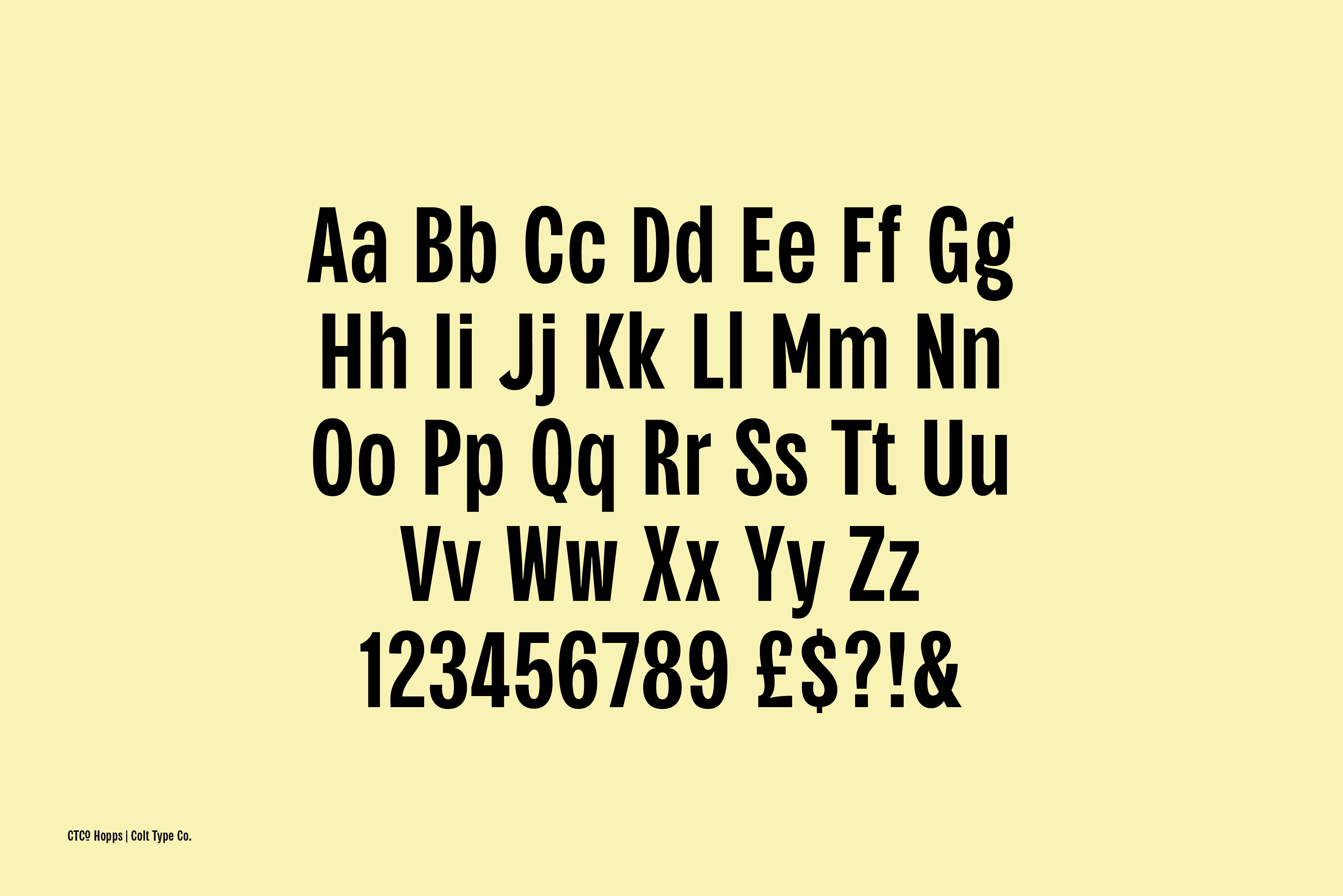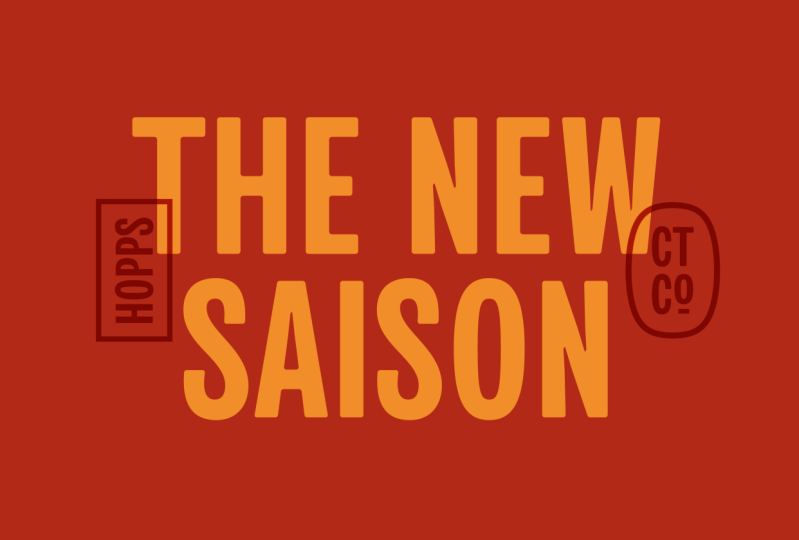
Conception de polices : Se lancer dans la création de polices avec les Glyphes 3 et la typographie
Apprenez à créer votre propre police à l'aide de Glyphs 3.
Si vous êtes novice en matière de création de polices et que vous souhaitez créer vos propres polices, rejoignez-moi pour apprendre à créer et à créer une police professionnelle Dans cette introduction à la création de polices avec Glyphs 3.
Dans ce cours, nous allons décomposer le processus en sections gérables ; de la création de votre dossier Glyphes, au dessin de lettres, en passant par la réalisation de composants réutilisables, en passant par l'espacement, le crénage et enfin l'exportation de votre police.
Si vous êtes nouveau sur Glyphs 3, ce cours est fait pour vous. Vous serez guidés de l'absence de Glyphs 3 à la création et à l'exportation de votre première police utilisée. Une certaine maîtrise de la création de formes vectorielles dans Adobe Illustrator ou similaire sera un avantage, mais pas absolument nécessaire.
• Introduction
• Le projet - Conception et création de votre propre police. Utiliser votre police d'une affiche typographique.
• Esquisse et inspiration - Rassemblez l'inspiration pour votre nouvelle police et réalisez des esquisses. Cela vous donnera une bonne idée de l'aspect de votre police et de la manière dont les lettres pourraient être faites.
• Paramétrer notre dossier glyphes - Nous allons vous expliquer comment paramétrer le dossier glyphes prêt à commencer à dessiner des lettres.
• Dessiner des glyphes carrés - Les formes de lettres sont classées en formes. Nous commençons par des formes carrées.
• Dessiner des glyphes ronds - Ensuite, nous dessinons les lettres rondes.
• Dessiner des glyphes triangles - Les lettres triangles suivent.
• Dessiner des glyphes hybrides - Utiliser les sections des lettres carrées, rondes et triangulaires
• Dessiner le S - Abordons le S qui semble plus compliqué qu'il ne l'est.
• Espacement et bardage - Nos dernières étapes, espacement et bardage permettront d'établir le flux de notre police.
• Tester et exporter votre nouvelle police - Test, test, test ! Utilisez votre police. Tout espacement étrange, tout glyphe écrasant et toute forme impaire se distinguera. Vous verrez que, lors de vos tests, vous affinerez vos formes de polices et votre espacement pour en faire une police belle et bien équilibrée.
1. Introduction: Dans ce cours, nous allons créer des polices san-serif en majuscules Je m'appelle Adam. Je suis designer de marque et je possède également une fonderie de caractères indépendante Il y a dix ans, j'ai commencé à créer des polices de caractères. C'est après avoir visionné le documentaire Helvetica que nous avons vu toutes ces fonderies et créateurs de caractères parler avec passion des polices de caractères , de la façon dont elles les fabriquent et de ce qui les inspire Et cela a déclenché quelque chose dans ma tête. J'ai soudain pensé que je pouvais aussi faire une chute. Sous ma voiture de fonderie à froid. J'ai probablement créé une vingtaine de polices, c'est loin. Et cela va des formes géométriques aux types de pinceaux. Si vous allez consulter mon profil, vous verrez des liens vers ceux qui s'y trouvent. Si vous êtes graphiste ou artiste de lettrage. Et en matière de conception de polices, c'est un très bon ajout à vos compétences . Ce cours s'adresse à tous ceux qui découvrent le logiciel de glyphes et la nouvelle conception des polices Ensemble. Pendant que nous créons notre police, nous passerons en revue le logiciel Glyphs et apprendrons à utiliser les fonctions de base À la fin du cours, vous aurez donc une très bonne idée du fonctionnement des glyphes, mais surtout, vous saurez comment créer une police rose. L'objectif est de vous donner une bonne introduction aux glyphes et de vous aider à démarrer votre aventure, il s'agit d'un design de police J'espère donc que tu me rejoindras. 2. Le Projet: Le projet Amen consiste à créer une police et nous allons le faire pendant que nous apprenons à utiliser les glyphes. Au fur et à mesure que nous apprendrons , nous construirons notre police Une fois créé, quel meilleur moyen de le mettre en valeur que de créer une affiche typographique ou peut-être même un ensemble de types de prothèses de produits. Ce que j'aimerais voir dans vos affiches, c'est quoi ressemble votre travail, à quoi il ressemble, comment se comporte-t-il et comment il agit ? Nous allons diviser ce cours en sections faciles. Nous allons commencer par dessiner et planifier notre police de caractères. Une fois que nous aurons réglé tout cela, nous configurerons notre fichier de glyphes Ensuite, nous allons commencer à créer notre ensemble de personnages principaux. Passons aux chiffres et à la ponctuation. Sans jeu de caractères complet, nous examinerons l'espacement et le crénage, puis passerons aux tests. Une fois que nous avons testé et exporté, c'est tout. Nous avons terminé. Nous avons notre police complète en classe. Suivez chaque leçon. Si vous voulez créer exactement le même style de police que moi, ou si vous vous sentez un peu plus aventureux, créez quelque chose de nouveau J'adorerais voir ce que tu trouveras. N'oubliez pas de télécharger la partie d'introduction depuis la section des ressources ci-dessous. J'ai ajouté quelques aide-mémoire qui vous aideront vraiment à démarrer dans l' apprentissage des touches de choc Cela vous aidera à accélérer votre processus dès maintenant et j'essaierai de me référer à ces clés au fur et à mesure. N'oubliez pas de créer un projet de classe. Montrez-nous que la nouvelle police que vous avez créée montre les affiches typographiques mettant en valeur votre police Je suis vraiment impatiente de voir ce que tu as fait. Si tu ne l'as pas déjà fait. Installons Glyphs Three pour le moment Un essai gratuit de 30 jours est disponible sur le site Web Et préparons-nous à MX Dot 3. Croquis et inspiration: Avant de commencer à concevoir notre formulaire, puisons notre inspiration dans des livres de typographie, des magazines ou des spécimens de typographie, ou même de n'importe quel endroit sur Internet où vous avez vu une belle topographie et fait quelques croquis Savoir où vous voulez que votre police soit utilisée et comment vous voulez qu'elle soit utilisée sera un énorme avantage lorsque nous concevons réellement dans Glyphs Un pack d'introduction est disponible à télécharger via Skillshare Dans le pack d'introduction, vous trouverez un modèle de carnet de croquis déjà des lignes de mesures Vous trouverez également un fichier de glyphes , préfabriqué avec tous les caractères que nous allons utiliser Et vous trouverez un aide-mémoire sur les glyphes avec toutes les touches de raccourci répertoriées Alors faites un croquis et quand nous serons prêts, nous configurerons notre premier fichier de police 4. Mettre en place notre dossier pour les glyphes: Commençons par créer notre fichier de glyphes. Tout d'abord, nous allons choisir Nouveau fichier et faire défiler la page jusqu'au latin. Donc, des glyphes non préparés pour vérifier les bases et créer un fichier Cette police sera uniquement en majuscules, nous allons donc supprimer les minuscules Dans le panneau de gauche. Vous pouvez passer en revue tous les caractères que vous souhaitez ajouter à votre police. Dans le téléchargement du pack d'introduction, vous trouverez le fichier de glyphes prêt à être utilisé qui a été préparé pour cette leçon Si vous ouvrez le modèle Eclipse à partir du pack d'introduction, voici ce que vous verrez Faisons-en profiter. Le panneau d'information. Je pense que l'alcool, c'est pour les fils d'Adam. Les unités par mètre conserveront milliers de versions, c'est juste au moment où vous modifiez la nouvelle version, assurez-vous d'ajouter un axe Y et de mettre à jour les fonctionnalités Sur le master. Nous pouvons voir le nom de notre maître. La nôtre est régulière. La façon dont nous allons passer à 400. Et vous pouvez également consulter les valeurs de nos métriques. Pour ce point, j'aimerais utiliser une valeur de dépassement d'environ 16 unités Pour chaque métrique. Il s'agira d'une bordure ou d'une marge. 16 unités. Pour le dépassement Il existe de nombreux plug-ins pour les glyphes. Et une chose que je ne peux pas faire, c'est montrer l'épaisseur de la tige. Donc, si vous allez dans Plug-in Manager, vous pouvez faire défiler la page vers le bas ou rechercher une certaine épaisseur de tige. Puis cliquez sur Installer. De toute évidence, je l' ai déjà installé. Donc, une fois que vous l'avez installé, redémarrez glyphs et il sera activé Et l'épaisseur de votre tige vous donne une idée de la façon dont la tige est une section. Pour celui-ci, vous pouvez voir qu'il s'agit d'une largeur de 146 unités. Vous pourriez tout simplement utiliser la règle. Mais c'est une chose supplémentaire que vous devez activer et désactiver. Alors que l' épaisseur de la tige du rivage est toujours la même. Et cela ne fait que rendre la vie un peu plus facile. Si vous ne voyez pas l'épaisseur de la tige Schar fonctionner. Accédez simplement à Afficher , puis activez Afficher l' épaisseur de la tige sous Afficher. Maintenant, configurons notre fichier et une fois qu'il est enregistré, nous sommes prêts à partir et les choses amusantes commencent. Donc, dans la prochaine leçon, nous allons voir comment créer nos glyphes carrés N'oubliez pas que si vous êtes bloqué à un moment ou à un autre, je suis disponible dans le panel de discussion sur Skillshare Je te verrai dans la prochaine leçon. 5. Dessiner des glyphes carrés: Il est bon de regrouper les glyphes par forme. Nous avons des rectangles, des cercles et des triangles. Si nous les regroupons, c'est parce que nous utiliserons des éléments de ces glyphes pour refaire d'autres Vous devriez toujours essayer de commencer par une haie. Il établit la largeur, la hauteur et l'épaisseur de la tige. découvrirons que la tige de la haie est la pièce que nous allons le plus souvent copier-coller dans de nouveaux glyphes Pour celui-ci, je vais utiliser une épaisseur de tige de 160. Je vais dupliquer cette tige pour créer les deux côtés de la haie. À l'aide des touches fléchées et de l'outil d'épaisseur de la tige. Nous pouvons parfaitement espacer nos tiges. Ajoutons maintenant la tige horizontale. Elle sera légèrement plus fine que la tige verticale. Pour l'équilibre optique. La tige verticale mesure un sixième, je vais donc taper 150 pour la tige horizontale En utilisant la barre d'espace, nous pouvons prévisualiser le vaisseau. Maintenant, nous avons fait la haie. Nous pouvons passer à la création de l'œil et d'autres personnages carrés. Copions cette tige de la haie et nous l'utiliserons pour fabriquer notre œil. Nous allons maintenant établir que E, F et L. Le F et le L partageaient la plupart des caractéristiques du genou. Nous allons donc commencer par un a. Encore une fois, en utilisant la haie. Nous utiliserons la tige de haie et la barre horizontale de la haie. Nous allons copier ce n vers le e pour voir si votre nœud est parfaitement aligné avec la ligne métrique. Et il affichera soit un cercle, soit un diamant. Un cercle signifie qu'il se trouve dans la limite du dépassement S'il y a un diamant, il correspond parfaitement au e et a l'air bien. Nous pouvons maintenant utiliser les éléments du E pour créer rapidement le F et le Al. C'est donc notre haie, E, F et L en colère, reste plus qu'un T. T. qui utilise exactement les mêmes principes que ceux que nous avons établis pour tout le reste ici. Je vous laisse donc le soin de le faire vous-même. 6. Dessiner des glyphes ronds: Pour faire nos lettres rondes, nous allons évidemment commencer par le 0. Et pour trouver la largeur et l' épaisseur, vous utiliserez la haie. En utilisant la haie comme guide, je vais faire un ovale. Pour des raisons d'équilibre optique, il est probable que vos lettres rondes aient besoin d'un certain dépassement Et c'est là que nos 16 points de dépassement entrent en jeu Maintenant, je vais dupliquer cette forme pour faire le compteur du, oh, je vais la redimensionner pour m'assurer qu'elle correspond à toutes les largeurs, ou même en sélectionner les deux parties Ou je découperai la forme en utilisant commande et le X et je la collerai à nouveau dans notre glyphe Les courbes sont actuellement téléchargées La courbe la mieux ajustée aide vraiment à égaliser ces courbes. L'idée qui sous-tend l'outil d'ajustement de la courbe est qu'il utilise une échelle de pourcentage pour modifier la quantité de courbe entre deux nœuds. À l'aide de la commande, de l'option, de la commande et des chiffres de un à huit, vous pouvez modifier la valeur de cette courbe d'ajustement afin qu'elle corresponde aux points situés sous les pourcentages dans l'outil de courbe d'ajustement Nous avons un petit problème avec la Terre. Il est rempli, et c'est parce que indications du chemin sont erronées. Nous pouvons le constater par les flèches pointant toutes deux vers la droite. Un intérieur doit aller dans le sens des aiguilles d'une montre. Un externe doit aller dans le sens antihoraire. Il existe plusieurs manières de modifier les directions du chemin. La première consiste à sélectionner le chemin. Cliquez avec le bouton droit et inversez les contours sélectionnés. Ou nous pouvons sélectionner tous les chemins dans le glyphe. Va sur le chemin. Et la bonne direction du chemin. Je préfère utiliser la bonne direction du chemin. Je pense qu'il vaut mieux laisser glyphes déterminer le chemin à suivre , car nous sommes maintenant sur la mer Intéressons-le en tant que composant. Je vais décomposer le 0 et en découper une section dans l'air pour former notre forme en C. Faisons la file d'attente. Encore une fois, nous allons l'ajouter en tant que composant, mais cette fois, il restera en tant que composant et nous n'y toucherons pas. Tout ce que nous allons ajouter, c'est la queue de la file d'attente. Le fait de conserver le composant signifie que si nous apportons des modifications à notre original, ces modifications seront également apportées dans la file d'attente. Je vais commencer par le C pour donner à notre G l' importance en tant que composant et le décomposer à nouveau. Nous pouvons prendre la tige horizontale d' une haie et la placer dans notre GI, aligner le tout et nous assurer que tout est beau, net et équilibré. Utiliser l'outil d'ajustement des courbes pour conserver la cohérence de toutes ces courbes 7. Dessiner des glyphes triangulaires: Dans cette leçon, nous allons examiner les lettres triangulaires. Pour moi, c'est a, V, K, M, N et W. J' aime commencer par un air pour mes lettres triangulaires. Je vais copier-coller la tige de la haie , puis l'incliner pour obtenir une diagonale parfaite. Utiliser la haie comme référence pour la largeur. Je vais déplacer la tige d'air dans la bonne position , la dupliquer, puis la retourner horizontalement pour créer l' autre côté de l'air. Lorsque vous assemblez deux lignes de cette façon, le haut peut paraître un peu plus gros que le bas Nous l'avons donc placé en haut pour lui donner un aspect plus équilibré et un peu plus uniforme. J'utiliserai la barre de la haie pour la placer en l' air et je la mettrai simplement en place. L'air semble un peu mince. Je pense donc que je vais déplacer ces lignes extérieures plus loin et réduire la largeur de la barre. Je veux que la section triangulaire de l'air soit aussi nette que possible, mais je voulais tout de même en avoir un certain contrôle. Je vais donc joindre les deux pièces. Mais avec ce nœud au milieu, je veux pouvoir contrôler indépendamment les angles gauche et droit. Et comme vous pouvez le constater, avoir un seul nœud n'est pas si simple. Nous pouvons donc utiliser un coin ouvert comme celui-ci pour simplement déplacer une section à la fois ou une ligne à la fois. C'est rarement utile dans les virages où vous devez déplacer des objets assez souvent. Cela signifie que vous ne déplacez qu'une seule pièce au lieu de deux pièces. Je veux que cette section soit exactement la même que le V. Je vais donc créer un composant à partir de cette pièce. Donc, si vous le sélectionnez, puis passez au composant depuis la sélection, puis que vous l'appelez quelque chose dont vous vous souviendrez. Et cela crée un nouveau glyphe. Ensuite, si nous passons à notre V, nous pouvons ajouter ce nouveau composant dans le glyphe Ensuite, sélectionnez-le et retournez-le horizontalement. Nous avons là notre B parce que c'est un composant. Si nous voulons changer quoi que ce soit pour l'air, se reflète également dans la façon dont j'aime les avoir sur LinkedIn de cette façon. Juste pour qu'il y ait une cohérence entre ces deux personnages. Pour le W, nous allons utiliser le même composant comme point de départ. Mais au lieu d'utiliser le composant tel quel, nous allons le décomposer Nous avons donc ces deux composants ici maintenant, mais nous ne pouvons pas les déplacer car ils prennent les valeurs de notre glyphe initial à partir de ce composant, Ces composants sont configurés pour s'aligner automatiquement. Si nous voulons les déplacer, nous devons désactiver l'alignement automatique. Si nous cliquons avec le bouton droit de la souris et que nous désactivons l'alignement automatique, cela nous donnera un contrôle total du mouvement. Nous pourrions donc simplement les assembler comme ça. Mais notre police est assez étroite. Cette version large de w aurait donc l'air étrange et déplacée. Donc, ce que nous allons faire, c'est le décomposer et écraser pour qu'il corresponde davantage au type que nous avons déjà créé. davantage au type que nous avons déjà créé Travaillons ensuite sur m et n. Je vais utiliser la haie pour déterminer la largeur de l'extrémité, correcte ? Réponse. Créez la section diagonale. Je vais le dupliquer, l'une des tiges et passer simplement sur les nœuds. Cela voudra être plus fin. J'aime donc simplement déplacer un peu plus les nœuds. Je trouve que ça a l'air plutôt bien. Je vais donc copier tout cela et m'en servir, la majorité d'entre eux. Mais évidemment, l'amnésique doit être un peu plus large. Pas trop loin là-bas. Nous venons de sortir de la marge. Mettons donc marge positive là-dedans , juste pour être sûrs de pouvoir voir ce que nous faisons. Je vais utiliser cette tige centrale, copier, la coller, puis la retourner horizontalement et la placer. Juste, et c'est ce que cette vérification permet de vérifier où tout se trouve. Ensuite, je veux fusionner tout cela. Retirez les deux nœuds situés en bas. Juste pour créer notre forme en M et y ajouter à nouveau un coin ouvert, il est toujours bon d'ajouter un coin ouvert où se trouve une section comme celle-ci. Il a l'air un peu large, donc je vais juste y apporter une touche. L'argent devrait être relativement facile. Je vais commencer par le Je n'ai pas besoin du jour. Il suffit de prendre la tige et le pied du R. Et nous allons juste les utiliser pour les soins. Comme vous pouvez le constater, la majeure partie s'y trouve déjà. Juste moi, déplace cette pièce à peu près au centre. Sélectionnez tout, copiez-le et collez-le, puis retournez-le verticalement ou horizontalement. Lieu de passe-temps. Très beau soin. J'en suis content. Pour terminer, je vais simplement fusionner ces deux pièces et les ajouter dans ce coin ouvert. Déplace ça dedans. Ensuite, nous y installerons également celui-ci. Juste pour donner l'impression que c'est vraiment connecté. Nous progressons vraiment bien et il ne nous reste que quelques lettres. 8. Dessiner des lettres hybrides: Viennent ensuite les lettres hybrides. C'est ici que nous combinons des éléments de nos glyphes carrés et des éléments de nos ascenseurs ronds pour créer des glyphes ronds carrés, tels que a, D, P, R et B. Je vais commencer par D en utilisant des sections de i, et nous allons créer cette forme en D. Je vais copier-coller ce que j'ai trouvé dans le D. Et en sélectionnant uniquement les nœuds de droite à partir du 0, les copier et les coller également dans le glyphe D. Une fois ceux-ci en place, je vais les réaligner. Nous n'avons pas besoin de dépasser un D, il suffit de nous assurer qu' ils sont parfaitement alignés Encore une fois, en utilisant cette forme de diamant comme référence. Je le ferai pour le haut et bien sûr pour le bas. Ensuite, nous devons étendre cette forme sur la droite pour en faire une forme solide pour le moment, elle n'est pas connectée. Nous devons donc nous assurer qu'il est connecté. Et nous le faisons avec le stylo. Et cela en utilisant la touche de raccourci P. Et tracez simplement quelques lignes et reliez cette forme. Je vais faire de même pour le bas. Sélectionnez le premier nœud , puis joignez le tout. Et vous pouvez voir que ce vaisseau a maintenant pris sa forme complète. Quand c'est rempli comme ça, vous pouvez voir que tout est connecté. C'est notre forme en D. Avec juste quelques ajustements, vous vous assurerez que tout est beau, équilibré et correct À partir du D, nous pouvons ensuite créer une forme de pois. Je vais copier-coller le D dans le p.ball. Je vais sélectionner cette courbe et redimensionner pour créer la courbe du p. J'utilise les flèches haut en bas pour obtenir toutes ces largeurs, C'est là que le plugin Shore Stem Thickness s' avère très pratique, car nous pouvons voir toutes ces épaisseurs lorsque nous déplaçons ces nœuds Nous n'avons pas besoin d'activer un autre outil pour le voir en peaufinant un peu plus ces nœuds Et nous sommes prêts à le faire. Essentiellement, le R n'est que le P avec une jambe. Nous allons donc ajouter le p. puis dessiner. J'aime bien, j'aime utiliser l'outil du rectangle. Ensuite, sélectionnez simplement les deux nœuds inférieurs et faites-les glisser vers l'extérieur. Toi et J, je vais m'en sortir avec la haie. En commençant par vous, je vais copier cette tige de la haie. Je vais copier le plus qui entre dans l'UE. Ensuite, j'utilise le 0 comme guide pour la largeur de l'UE. Ensuite, nous allons construire le u en utilisant ces sections. Le bas de l' UE est trop haut. C'est parce que nous l'avons emprunté au R. Ce que nous voulons, c'est qu'il ressemble davantage à la courbure du d. Et nous pouvons le faire en ramenant les nœuds un peu plus près du bas. Ensuite, en utilisant notre outil de courbe d' ajustement, qui est Control Option Command. Et j'en utilise sept. Nous pouvons rendre ces courbes belles et nettes. Encore une fois. Pour créer le j, nous pouvons utiliser le u. Copiez-le et collez-le en l'air. Ensuite, nous allons simplement supprimer les nœuds de gauche Coupe-le juste là, en angle. Supprimez-les et ils auront notre J. Pour le y. Nous allons réutiliser notre composant. Nous allons le retourner puis le décomposer. C'est. On dirait ces nœuds et mettez-les en position. En utilisant la tige de l'œil. Nous allons copier-coller ces deux objets dans notre centre y. Ensuite, je vais nettoyer ces deux nœuds et nous aurons un y à ajouter Utilisons un t. Je vais copier-coller le haut du T et le dupliquer vers le bas pour le zed. Copiez ensuite le radical du T et utilisez-le pour la partie diagramme de cette annonce. Et x peut être assez difficile à créer. Mais pour ce style de police, je préfère utiliser la forme diagonale que nous avons déjà créée, la décomposer puis la réduire. Je vais ensuite le copier et le coller en place, en le reproduisant essentiellement pour créer un X. Sélectionnez tout, assurez-vous qu'il correspond à la hauteur du capuchon. Une fusion. N'oubliez pas de remettre ces coins ouverts une fois de plus. Je vais juste tout emménager pour qu'il convienne. Le reste de la police. Je vais les mélanger et créer de très jolis 9. Leçon 8 Le S: S peut être une autre lettre difficile, mais décomposons-la en sections. Nous allons utiliser un C. Nous n' utilisons que la partie supérieure de la mer. Nous allons donc le copier-coller et déplacer ces nœuds en place. Nous allons corriger ces courbes douteuses en utilisant la méthode de la courbe d'ajustement Maintenant, copiez-collez notre haut dans le bas. Il suffit de le retourner et de le placer dans la zone de dépassement Nous devons maintenant réunir ces deux pièces. Nous allons donc créer un lien entre le haut et le bas. Lorsque nous aurons mis en place un lien de base, tout le groupe émergera-t-il dans son ensemble. À ce stade, c'est une bonne idée de corriger la direction du chemin. Ces nœuds carrés bleus indiquent qu'il peut s'agir de coins. Donc, ce que nous voulons faire, c'est double-cliquer dessus et les transformer en lignes continues. Cela facilite le flux de la lettre. Il ne nous reste plus qu' à mettre nos nœuds et bras en place pour faire de beaux numéros Nous avons maintenant dessiné toutes les lettres majuscules. Nous avons toutes les connaissances nécessaires pour créer le reste de nos personnages. Je vous laisse donc le soin des chiffres et de la ponctuation. Et je te reverrai ici pour l'espacement et le crénage 10. Espacement et crénage: Nous avons donc maintenant toutes nos lettres en place. Nous pouvons maintenant commencer, l' espacement est bon d' utiliser des groupes d'espacement. Nous allons donc utiliser la haie et un R et un V, ou un héritier, pour créer de l'espace en groupe. Pour nos glyphes rectilignes, je vais utiliser Hedge Pour une haie. Donnons-lui une valeur de six jours. Nous le ferons pour les deux parties. Et un moyen simple de reproduire les deux versions consiste à utiliser des valeurs égales. Et cela prendra la valeur du côté gauche et l'utilisera également du côté droit Nous pouvons maintenant appliquer la même valeur, couverture, à i, m et n. En sélectionnant tous ces caractères, nous pouvons descendre en bas à gauche et saisir les valeurs de ces roulements latéraux. Nous allons simplement saisir « haie » dans les deux valeurs des roulements latéraux. Nous pouvons donc voir ici que le nombre de favoris est égal à celui d'une haie , soit 60 points Pour nos lettres rondes, nous utiliserons le R. Nous pouvons soit y mettre une valeur numérique, soit utiliser notre valeur comme norme pour les autres lettres incurvées. Ou nous pouvons utiliser une équation. J'aime parfois utiliser. La moitié de la haie. Mettez fin à l'équation de h sur deux, ce qui nous donne alors 30 points. Encore une fois, sur le côté droit, barre égale nous donnera également une valeur de 30 points sur le côté droit Il suffit de les tester en appuyant plusieurs fois sur la haie. Nous pouvons voir à quoi ressemblent ces espaces. Nous pouvons appliquer les valeurs à Q, C, G, zéro et parfois à un S, selon la proximité de la courbe avec un 0. Je vais utiliser V comme maître. Mais il ne faut pas oublier de désactiver l'alignement automatique dans cet air libre Et le V. A V possède beaucoup d'espace négatif. Nous allons donc lui donner une petite valeur sur les roulements latéraux. Nous pouvons appliquer cela au y et à l'air, et parfois aussi au w, au x et au t. Et ils nous permettent d'utiliser la valeur de haie sur le côté droit et la valeur 0 sur le côté incurvé pour les côtés valeur de haie sur le côté droit et la valeur 0 sur droits. Bien entendu, vous pouvez simplement utiliser des valeurs pour les glyphes de votre choix Vous n'êtes pas obligé de les regrouper. Je trouve juste que cela nous facilite beaucoup la vie si nous avons des groupes sur le L. Je me débrouille tout seul avec 16. Mais sur le côté gauche, il a une valeur de couverture Parce que W a un espace négatif légèrement inférieur un V. Mais nous voulons tout de même utiliser la valeur V. Nous pouvons simplement utiliser une équation comme V plus dix. Et cela nous donnera la valeur v avec dix points supplémentaires Lors de l'espacement, vérifiez régulièrement les caractères. Appuyez sur la commande Option F pour afficher les chaînes de texte. Ils sont très utiles pour vérifier espacement et voir s'il vous manque des glyphes Comme pour les groupes d'espacement, nous pouvons également créer des groupes de crénage Vendons des groupes de crénage. Donc, pour une, je vais donner de l'air à ce groupe de comptabilité. Cela peut également s'appliquer au y ou au T. Et pour v, je vais lui donner une valeur de crénage, notre groupe comptable de v également Ensuite, entre le a et le v, nous pouvons faire en sorte que ce soit -20 ou peut-être plus. Il faudra peut-être plus que cela. Si nous regardons le bas de notre panneau de glyphes, nous pouvons modifier le flou du texte. Et cela nous permet de voir l'espace négatif entre chaque lettre. Comme vous pouvez le voir ici, il y a un peu trop de distance entre le a et le v par rapport à la haie et à la haie. Faisons donc en sorte que ce point soit défectueux, juste pour réduire un peu plus cet écart. C'est une très bonne technique juste pour voir quels sont ces espaces négatifs. Maintenant, nous allons faire correspondre l'autre côté du V et l'air. Et évidemment, cela devrait être un -40. Si nous tapons a et V plusieurs fois, nous pouvons voir que cet espacement est cohérent Maintenant, nous allons faire le W. Si nous appliquons la valeur du groupe V à w, nous pouvons voir que cela la fait également entrer de -40 Cependant, je pense que c'est peut-être un peu trop. Donnons donc ceci, c'est basé sur la valeur, et nous allons faire en sorte que ce soit -30 Et faites de même sur le côté droit. Le courant des groupes peut être appliqué à n'importe quelle lettre. Appliquons donc le groupe V au y. Vous pouvez voir que cela donne les mêmes valeurs que pour le V et l'air. Nous allons donc nous frayer un chemin en créant du courant par paires et en créant des groupes au fur Cornyn et espacement protègent le temps et nécessitent également de nombreux tests Au fur et à mesure, nous testons les lettres et les chaînes de mots les unes à côté des autres, puis nous les ajustons et les affinons Il s'agit toujours de peaufiner et de peaufiner. Nous ne pouvons pas nous attendre à trouver exactement le bon résultat du premier coup . Nous apportons donc progressivement meilleurs changements et parfois certains changements ont un impact sur d'autres. Mais la création de groupes de crénage facilite un peu la gestion Ensuite, nous allons faire quelques tests, exporter la police et l' essayer dans Illustrator 11. Tester et exporter votre nouvelle police: Nous avons fait beaucoup d'entrée de courant et d'espacement, et il est maintenant temps de vraiment le tester Nous devons donc rédiger une lettre. Nous allons appuyer sur commande Option F pour afficher les chaînes, les chaînes de texte. C'est là que nous voyons rarement comment ces spécimens ont été affectés. Si nous avons besoin de changer quoi que ce soit, parcourez autant de chaînes de texte que possible. Plus vous trouverez de combinaisons de lettres, de mots et de phrases, mieux c'est. que je trouve toujours, c'est que lorsque je commence à Ce que je trouve toujours, c'est que lorsque je commence à l'utiliser et à taper dans Illustrator ou InDesign, je trouve toujours quelque chose que je n'ai pas remarqué lors de la création de la police Vous finirez donc toujours par revenir arrière et peaufiner quelque chose jusqu'à ce que vous trouviez toutes les petites pièces que vous avez manquées Avant de faire la barre X, ajoutons quelques paramètres personnalisés supplémentaires à notre police Nous allons ajouter un faux contrôle de compatibilité. Ceci ne fait que résoudre tous les problèmes de compatibilité. Et ajoutons également les fonctionnalités d'audit. Juste au cas où nous oublierions d'ajouter des fonctionnalités avant d'exporter. Cela l'incitera à le faire car la barre X est une solution de sécurité intégrée Donc, avant d'exporter moins de leurs fonctionnalités, juste au cas où il y aurait quelque chose qui devrait être mort. Nous n'avons aucune fonctionnalité de type ouvert ni aucun caractère spécial. Rien n'a donc besoin d'être mis à jour. Mais juste pour de bonnes pratiques, je cliquerai dessus de toute façon. Maintenant, avec toutes les fonctionnalités de Dead and Double Check sur le panneau d'information, nous pouvons exporter notre fichier RTF Cliquez sur Exporter, trouvez l'endroit vers lequel vous souhaitez l'exporter. J'aime créer un dossier d'exportation. Puis cliquez sur Ouvrir. Assurez-vous qu'il s'agit d'un post-scriptum. Nous devons vérifier le RTF. Si ce n'est pas du RTF. Si vous souhaitez exporter pour le Web, vous pouvez utiliser les WR FF et les W ou F, F2 Avant d'exporter, assurez-vous que suppression, de superposition et d'indication automatique sont toutes deux cochées. Et c'est tout. Nous avons exporté notre police. Et ici, vous pouvez voir le RTF Adam sans normal. Pour installer des polices. J' aime beaucoup utiliser les polices de caractères. C'est un client de polices de caractères. Cela signifie simplement activer et désactiver les polices. C'est juste un petit peu plus facile. La police et la base de polices. Il suffit de le faire glisser et de rechercher votre police. Les fils d'Adam, et allumez-le en utilisant ce petit point. Le point vert indique qu'il est actif. Et si nous nous lançons dans Illustrator, exemple dans une zone de texte et que nous cherchons une police, augmentons la taille des points et vous pouvez voir à quel point c'est beau. Essayons de taper un peu. Heure. Les fils d'Adam. Si je peux épeler, alors nous sommes la preuve que cette erreur fonctionne 12. Félicitations et merci !: Félicitations, vous venez de créer votre toute première police dans Glyphs Three Merci beaucoup d' avoir participé à mon cours. J'espère que cela vous a plu. N'oubliez pas d'ajouter votre projet à Skillshare. Et si vous avez des questions, utilisez la section de discussion de Skillshare et je vous recontacterai Mais encore une fois, merci beaucoup d'avoir suivi mon cours et je vous verrai dans le prochain.